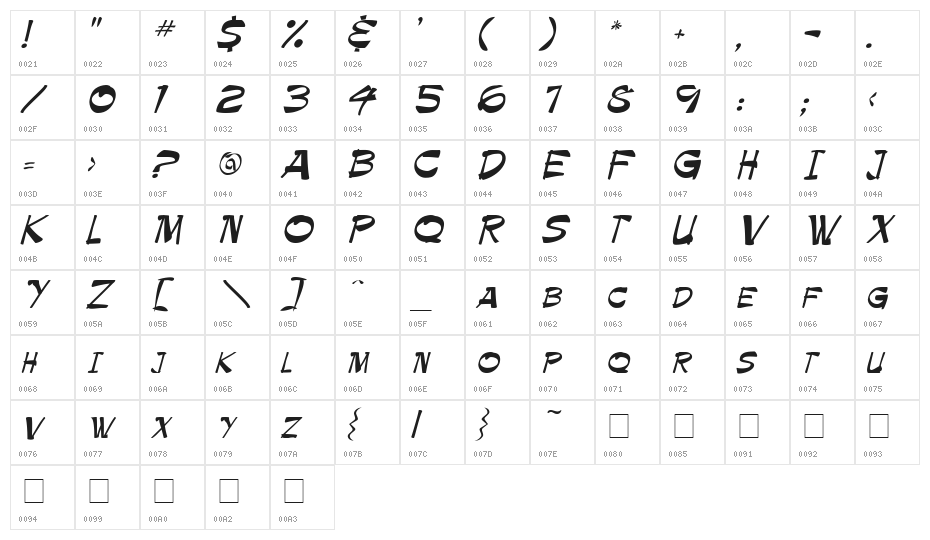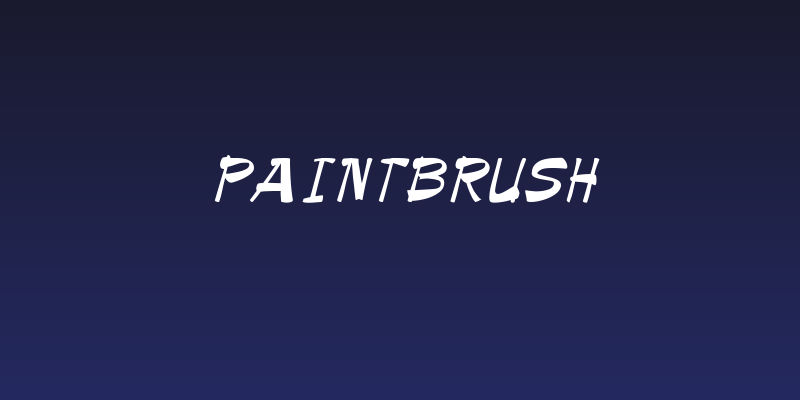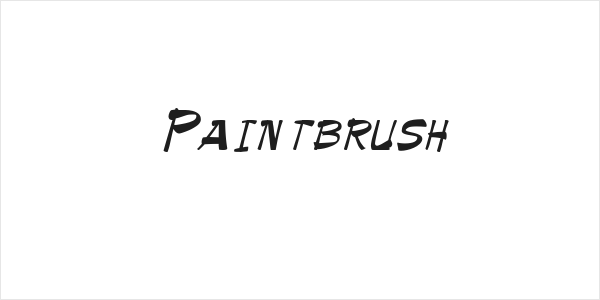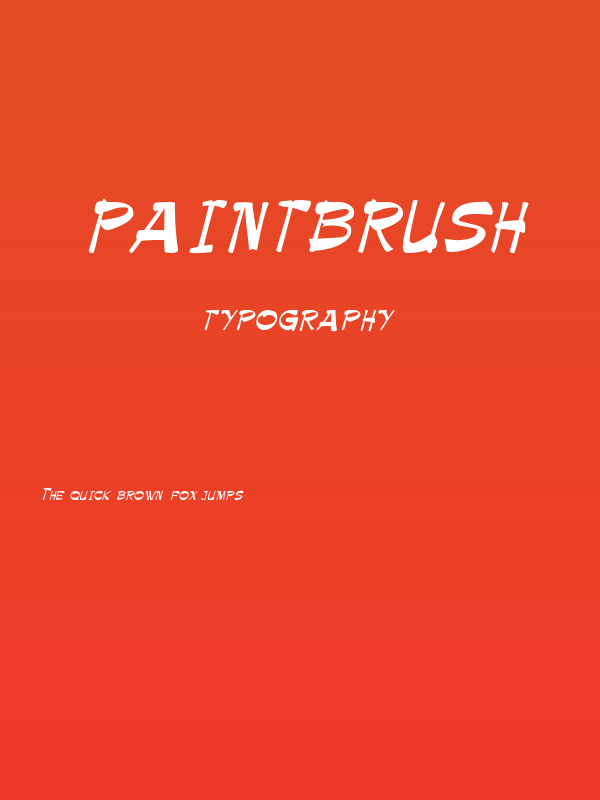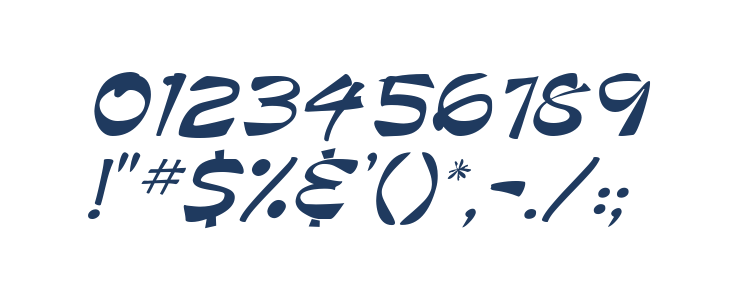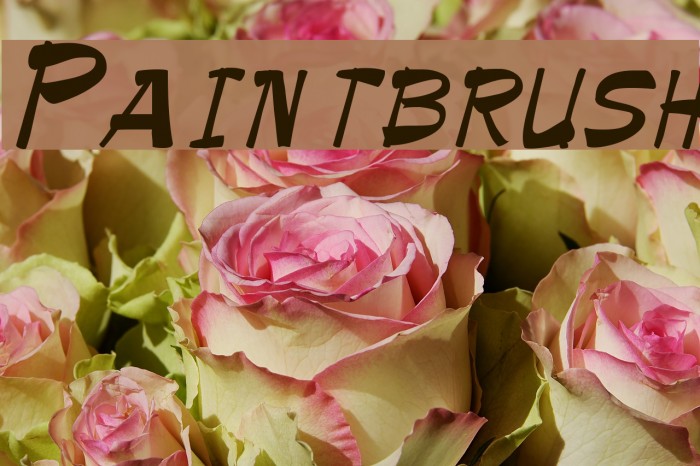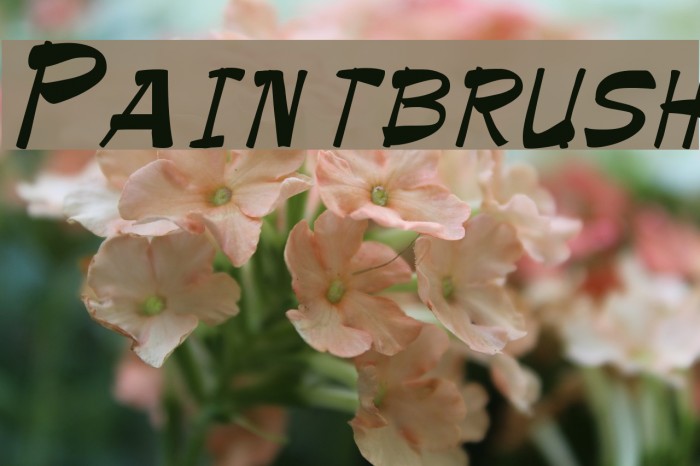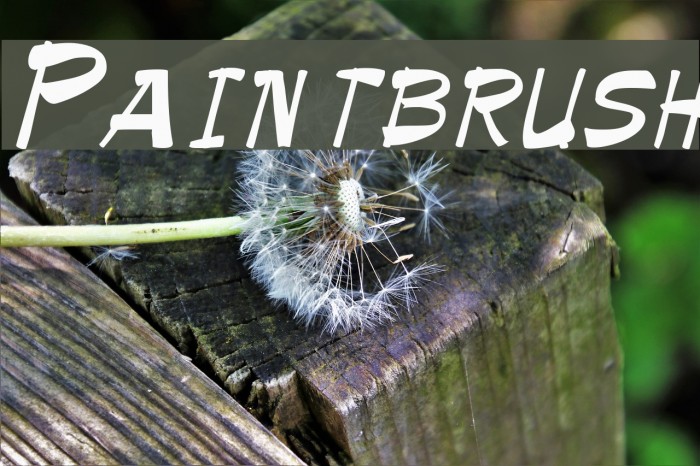
Paintbrush Font
| Stile generale | Artistic, Expressive |
| Progetti proposti | Ideal for creative projects such as posters, art exhibitions, branding for artistic ventures, and any design requiring a bold, expressive touch. |